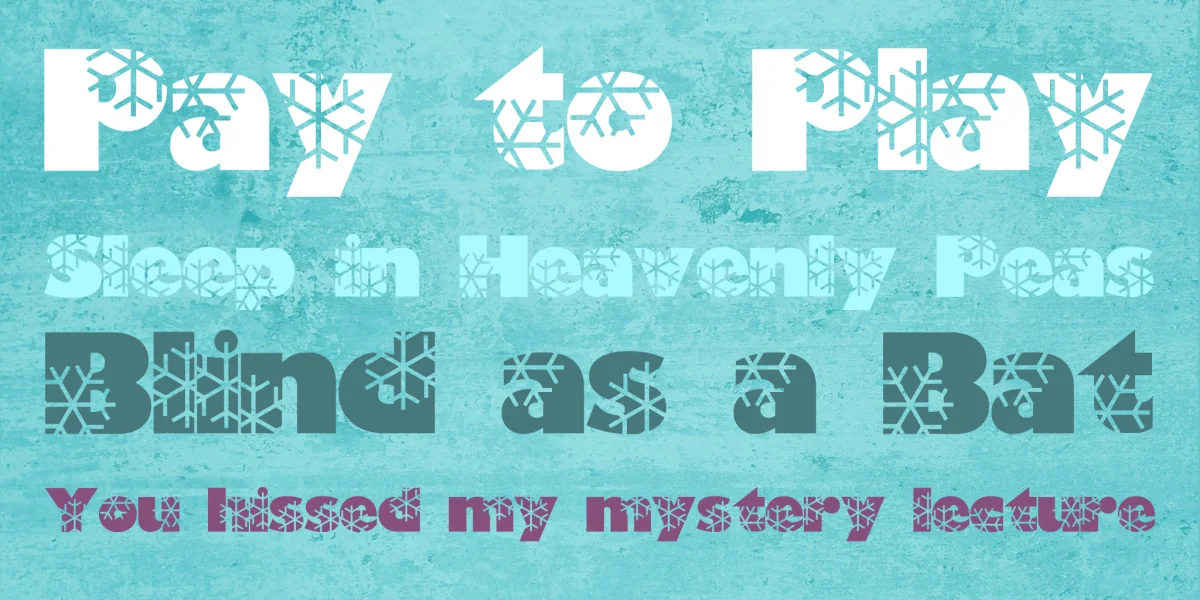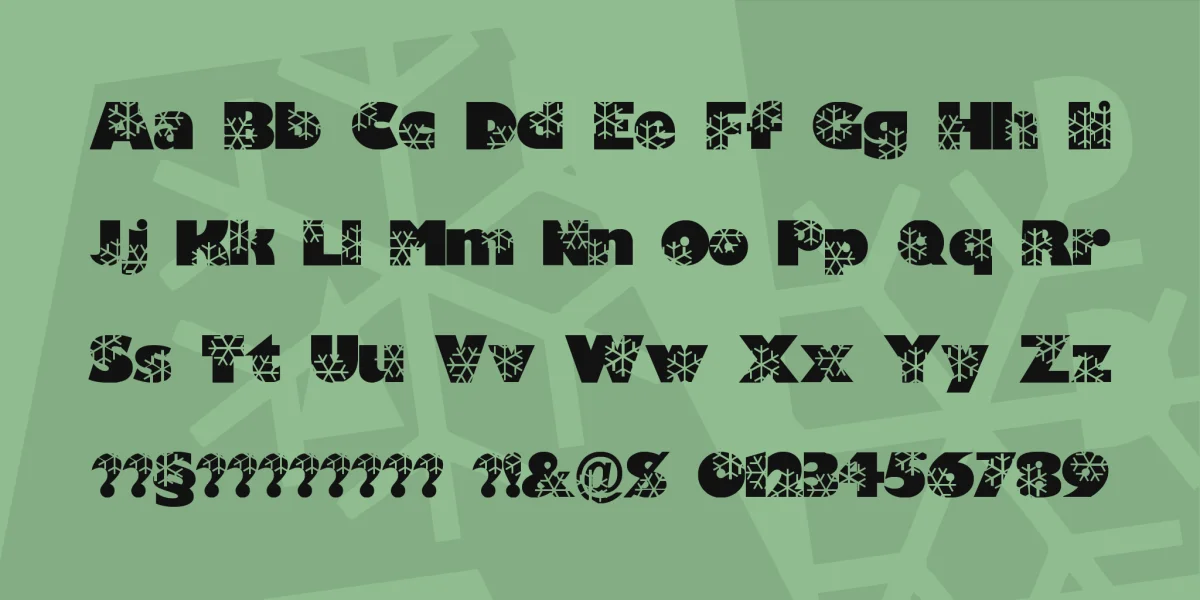
Diese beiden Schriften basieren auf Gill Sans Ultra Bold [Condensed], ich habe sie vor Jahren mal für Überschriften gemacht. Krystal passt wunderbar in den Winter, und Hole-Hearted kannst du dann am Valentinstag verwenden ;)